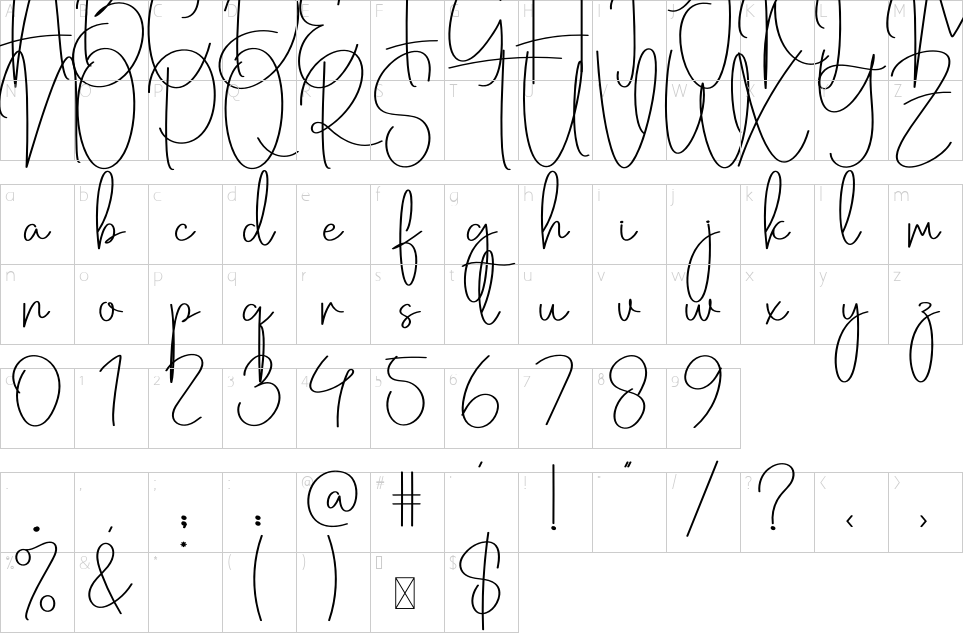
Scary Atmosphere Font | 1001 Free Fonts – Download Grátis
A fonte “Scary Atmosphere” oferece um ambiente capturador e envolvente que pode transformar qualquer ambiente em algo sobrenatural. Desenvolvida por scratchones, essa fonte criativa foi projetada para criar um efeito perturbador e impressionante. Com seus traços intricados e nuances distintas, ela é perfeita para criar uma atmosfera de suspense e terror em design gráfico, seja para anúncios, materiais de marketing ou até mesmo para personalizar mensagens de e-mail. Com seu design único e eficiente, “Scary Atmosphere” é uma fonte gratuita e de alta qualidade, disponível para download em Windows e Mac. Seja você um artista digital ou designer gráfico, essa fonte trará um toque inovador ao seu trabalho.